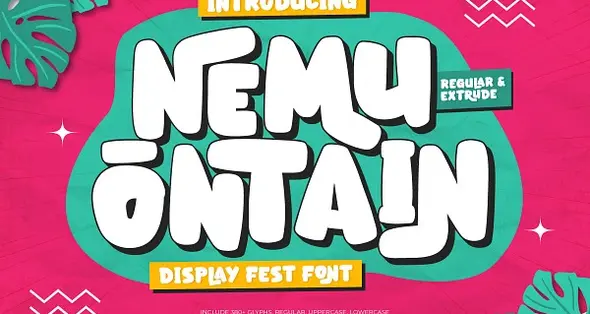
• Nemu Ontain - Display Fest Font
فونت انگلیسی فانتزی کودک
• circle سایز پیشنهادی: تیتر، کتاب کودک
• circle سبک قلم: Serif
• circle لیگچر
با تایپوگرافی پرانرژی و آماده فستیوال، بیانی قدرتمند داشته باشید! «نمو اونتین» یک فونت نمایشی (Display) جسور و سرزنده است که انرژی مهارناپذیر فستیوال‌های موسیقی و فرهنگ خیابانی در آن موج می‌زند. این فونت برای جلب توجه طراحی شده و با کاراکترهای اکسپرسیو و افکت اکسترود (Extrude) خیره‌کننده، هر واژه را به یک تیتر اصلی تبدیل می‌کند. این تایپ‌فیس حس شادی خالص، آزادی و سرگرمی فراموش‌نشدنی را به پروژه‌هایی که جرأت متفاوت بودن دارند، تزریق می‌کند.
این خانواده فونت قدرتمند با دو استایل برجسته Regular و Extrude ارائه می‌شود که به شما انعطاف‌پذیری نهایی را برای خلق تایپوگرافی پویا با عمق و حرکت می‌دهد. استفاده از این فونت در پروژه‌های مختلف انجام می‌شود و استایلی spectacular به طرح‌های شما می‌بخشد.
ویژگی‌های اصلی:
• شامل بیش از ۳۶۰ گلیف (Glyphs)
• دارای حروف بزرگ، کوچک، اعداد و علائم نگارشی
• شامل حروف جایگزین (Alternates) و لیگاتورها
• پشتیبانی گسترده از بیش از ۸۵ زبان دنیا
موارد استفاده:
• پوسترهای کنسرت و رویدادهای موسیقی
• طراحی کالاهای فستیوال (Merchandise)
• برندینگ‌های پرانرژی و تبلیغات خیابانی
• کاور آلبوم و گرافیک شبکه‌های اجتماعی
MAKE A LOUD STATEMENT WITH ENERGETIC, FESTIVAL-READY TYPOGRAPHY.
Nemu Ontain is a bold and spirited display font, dripping with the untamed energy of music festivals and street culture. Designed to command attention, its expressive characters and striking extruded effect make every word a headline act. This font brings a vibe of pure joy, freedom, and unforgettable fun to any project that dares to be different.
This powerful font family comes with two standout styles—Regular and Extrude—giving you the ultimate flexibility to create dynamic typography with depth and movement. Packed with over 360 glyphs, including uppercase, lowercase, numerals, alternates, ligatures, punctuation, and extensive multilingual support, Nemu Ontain is the perfect choice for concert posters, festival merchandise, high-energy branding, album covers, social media, and any project that needs a bold, artistic edge.
Elevate your design from standard to spectacular with Nemu Ontain—a font that’s energetic, solid, and full of style!